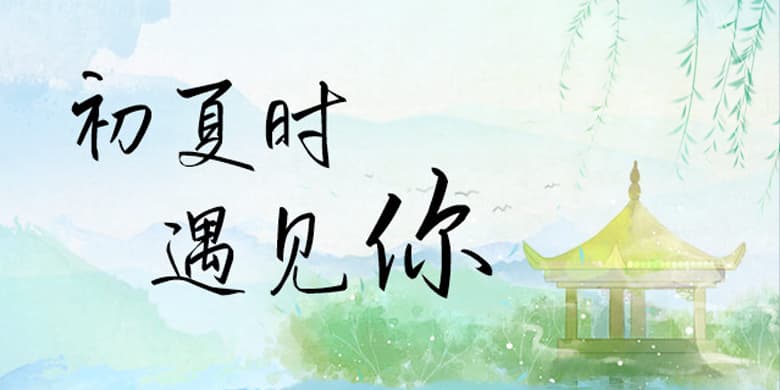
品牌:方正手迹设计师:尚正中发行时间:2020字库编码:大陆简体(GB2312-80)分类:常规书写·硬笔字体属性:精品字
初夏时遇见你这款字体用笔细腻,笔画舒展,提按顿挫极具古意,传统书法与现代气息兼备,端庄优雅韵味十足。适用于文化类宣传、文艺类的书刊、品牌广告和产品包装设计,综艺影视用字,以及社交网络的个性化用字。